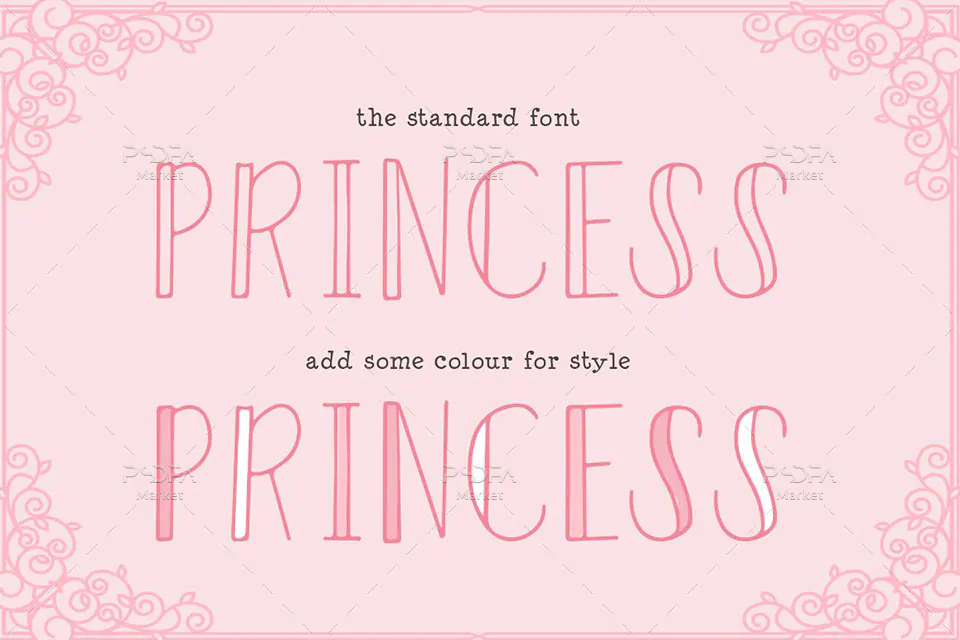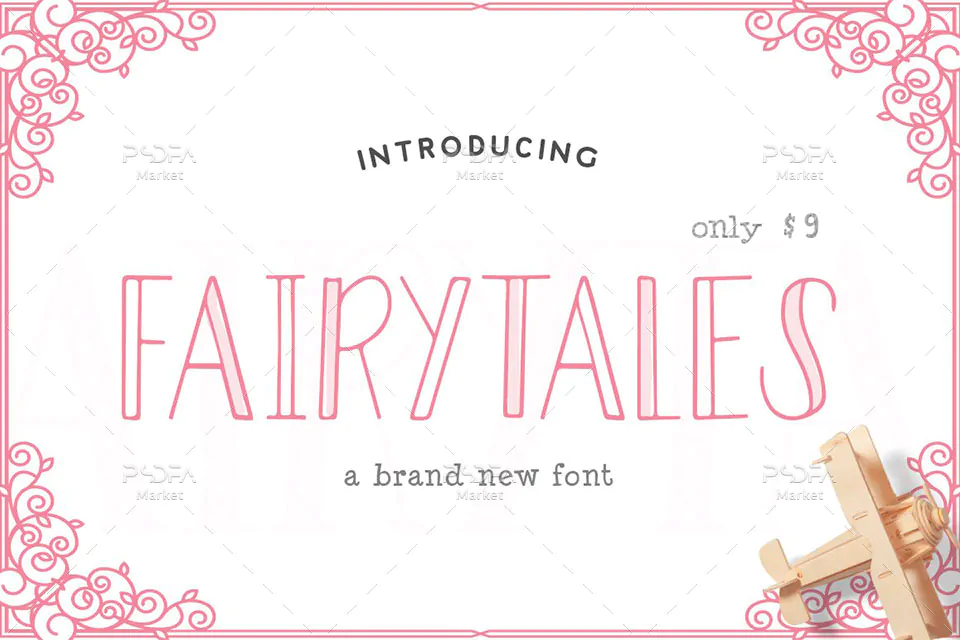
فونت دستنویس توخالی کودکانه و فانتزی Fairytales
فونت دستنویس توخالی کودکانه و فانتزی Fairytales یک قلم فوق العاده زیبا است که مناسب جهت استفاده در طرحهای گرافیکی مختلف به خصوص طراحی انواع طرحهای کارتونی و کودکانه میباشد. این فونت زیبا در قالب یک فایل OTF در فایل محصول قرار دارد که با نصب آن در پوشه فونتهای سیستم میتوانید از این فونت انگلیسی در تمام نرم افزارهای گرافیکی و تایپ متون همچون فتوشاپ، افتر افکت، پریمیر، ورد، پاورپوینت و … استفاده کنید.
فونت دستنویس Fairytales در وزن معمولی (Regular) طراحی شده است که میتوانید از آن در طراحی انواع کارت تبریک، کارت پستال، کارت ویزیت، کاور آلبوم موزیک، طراحی انواع بنر، پوستر، تراکت، تقویم و دیگر طرحهای گرافیکی استفاده کنید.